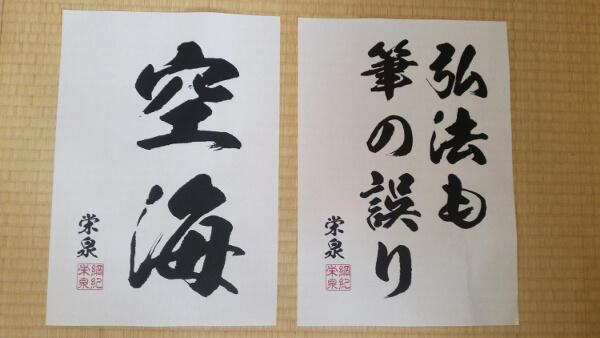
鬼滅の刃も際立たせた一筆!綱紀栄泉の芸術的PCフォント【昭和書体】
老舗の入り口を飾る手書き毛筆の木製看板。
文字だけで店の存在感を強調する木製看板は日本ならではの趣があり、ひとつひとつの文字に書家の魂がこもっているからでしょうか、その看板は時間の流れと共に味わいが増していきます。
しかし、時代が変わり、看板を製造する広告業者が扱う書体はゴシックや明朝などのPC書体が主流になりつつあり、手書き文字の時代からマシン出力の時代へと移行しています。
便利になるその一方で、筆で文字を書く機会が激減してしまい、活字はもとより楷書、行書を代表とする毛筆書体を書きこなせる職人がいなくなるのではないか、と危惧した昭和書体は、かつて看板職人であった書家の綱紀栄泉氏の書き綴った毛筆諸本をデジタル化することで本格毛筆フォントを後世に残すことを考えました。
その作業は気の遠くなるようなものでした。
フォント41種類の偉業!綱紀栄泉の世界
そもそも1人の書家が、41種類もの形態の異なる毛筆書体を書き上げた例は聞いたことがありません。
PCフォントとなると第一水準から第二水準まででおおよそ7,000文字が必要で、41書体に書き分けた文字が約29万字。書き直しを含めると2倍近くにものぼるそうです。
齢80歳の書家の綱紀栄泉氏は、現在もあらゆるニーズに対応する書体を目指すべく鋭意制作中とのこと。
伝統を最新技術に「MORISAWA」
昭和書体で販売中である「昭和楷書」「銀龍」「闘龍」「黒龍」「陽炎」の5書体はPCフォントでありながら、まるで直筆文字と見間違うほどのリアルなかすれや筆勢を残しており、A4用紙にプリンターで印刷したものはまるで手書きの文字であるかのようです。
言葉や文字は時代で大きく変わっていきます。テクノロジーを使って今の時代の文字を後世に残すことは非常に大切な取り組みなのかもしれません。